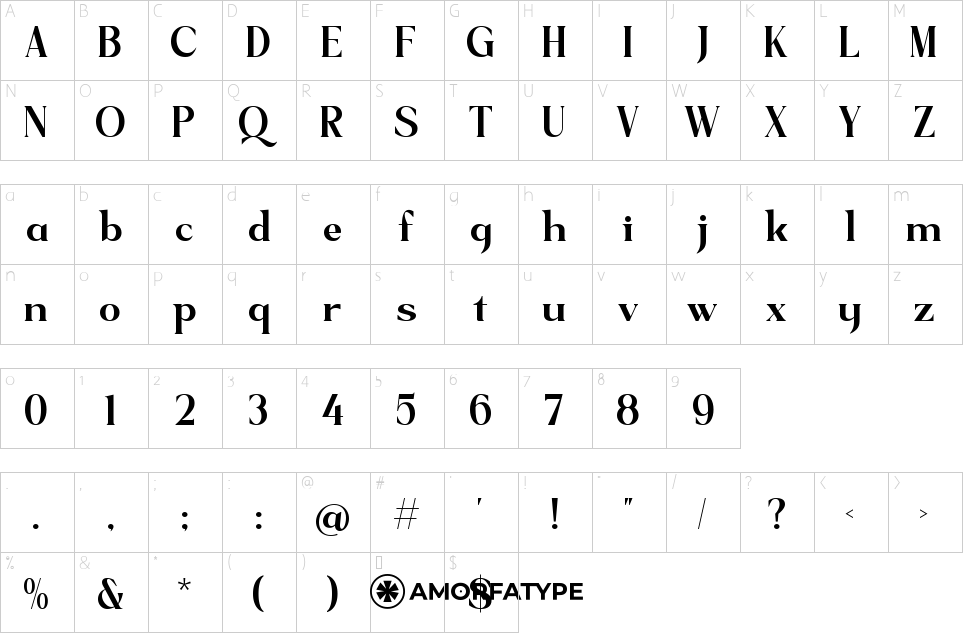
Sagfield é uma elegante e versátil fonte para escrita de texto, desenvolvida pela Amorfa Type. Esta fonte é perfeitamente adaptada para uso em um vasto número de aplicativos, desde websites até editoras de texto e design gráfico. Com sua tipografia clean e agradável, Sagfield oferece um estilo moderno que se adequa perfeitamente a textos de diversos tamanhos e contextos. Seja para aplicativos pessoais ou corporativos, Sagfield é uma escolha confiável para quem busca uma fonte grata e de alta qualidade. Com a facilidade de download disponível para sistemas Windows e Mac, você pode experimentar sua beleza e elegância em seu próximo projeto.